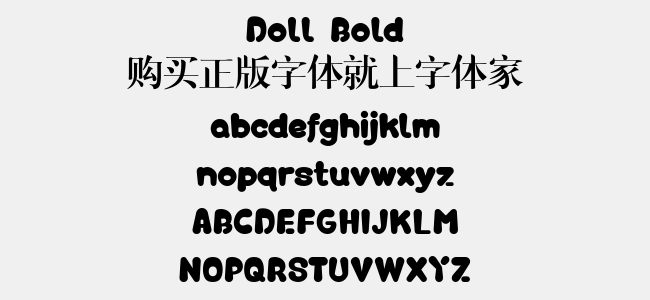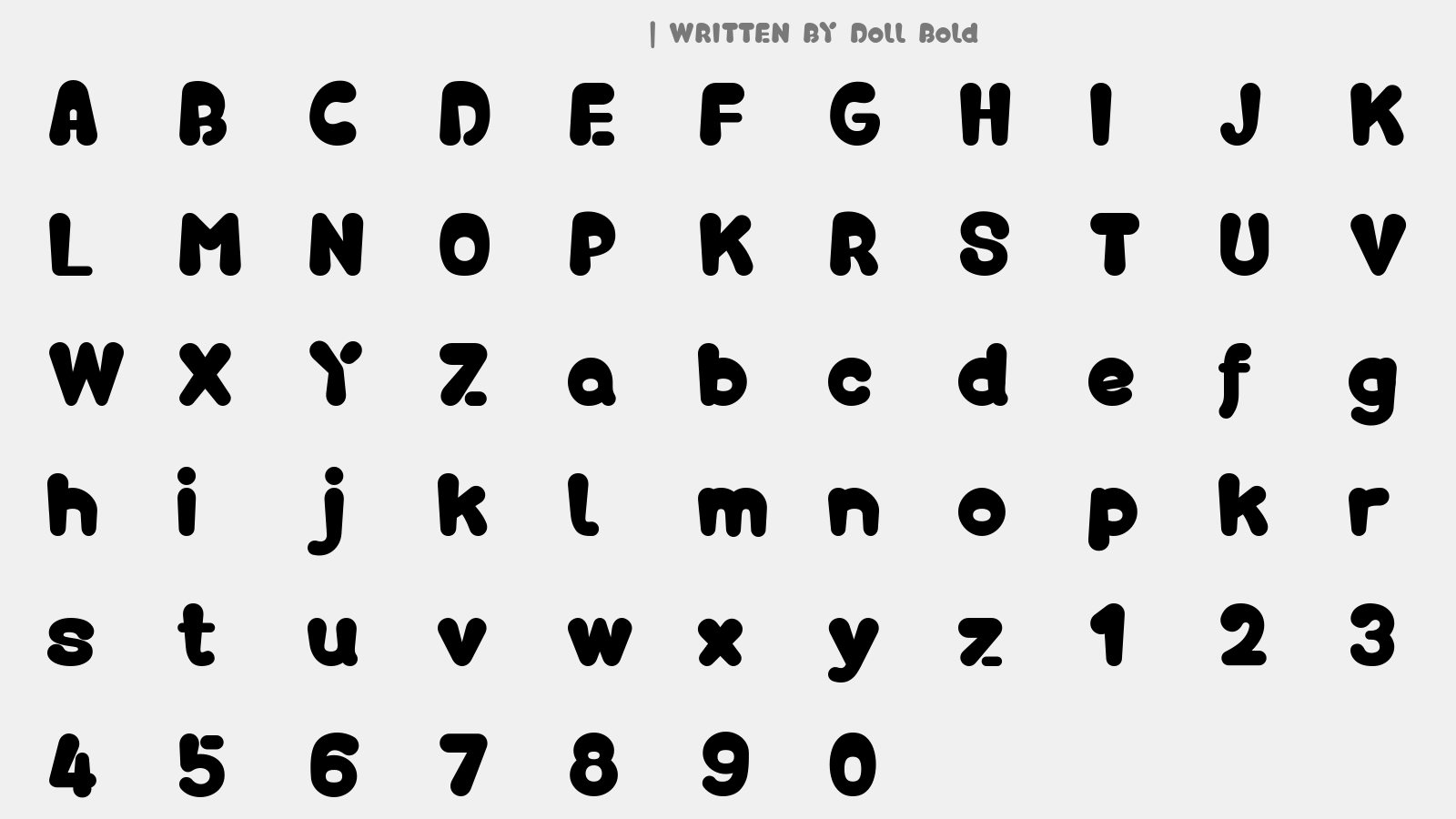
Doll Bold
字体名称:Doll Bold
字体字数:26个英文大小写字母及和阿拉伯数字
书体类型:英文类
Doll Bold
Doll Bold是一款个性独特的英文字体,非常适合创意类的PS字体,英文广告设计载体上使用,在设计中选择这款字体应用的话,会起到非常理想的效果。此款字体适用于个人学习交流,字体研究以及一些非商业用途的载体中,由三极字库出品,字体家平台整理发布。
Doll Bold - 大写字母/小写字母/数字